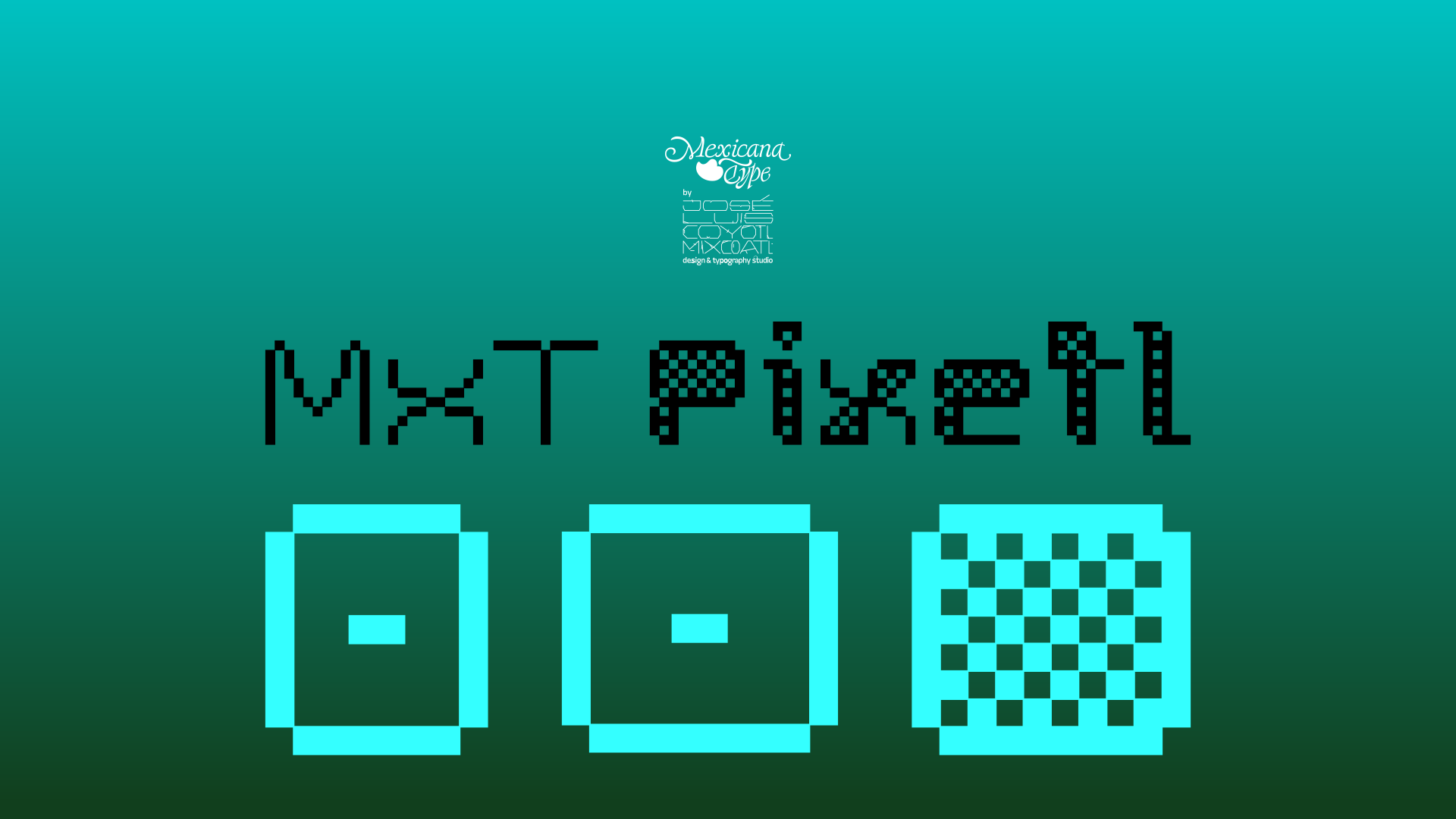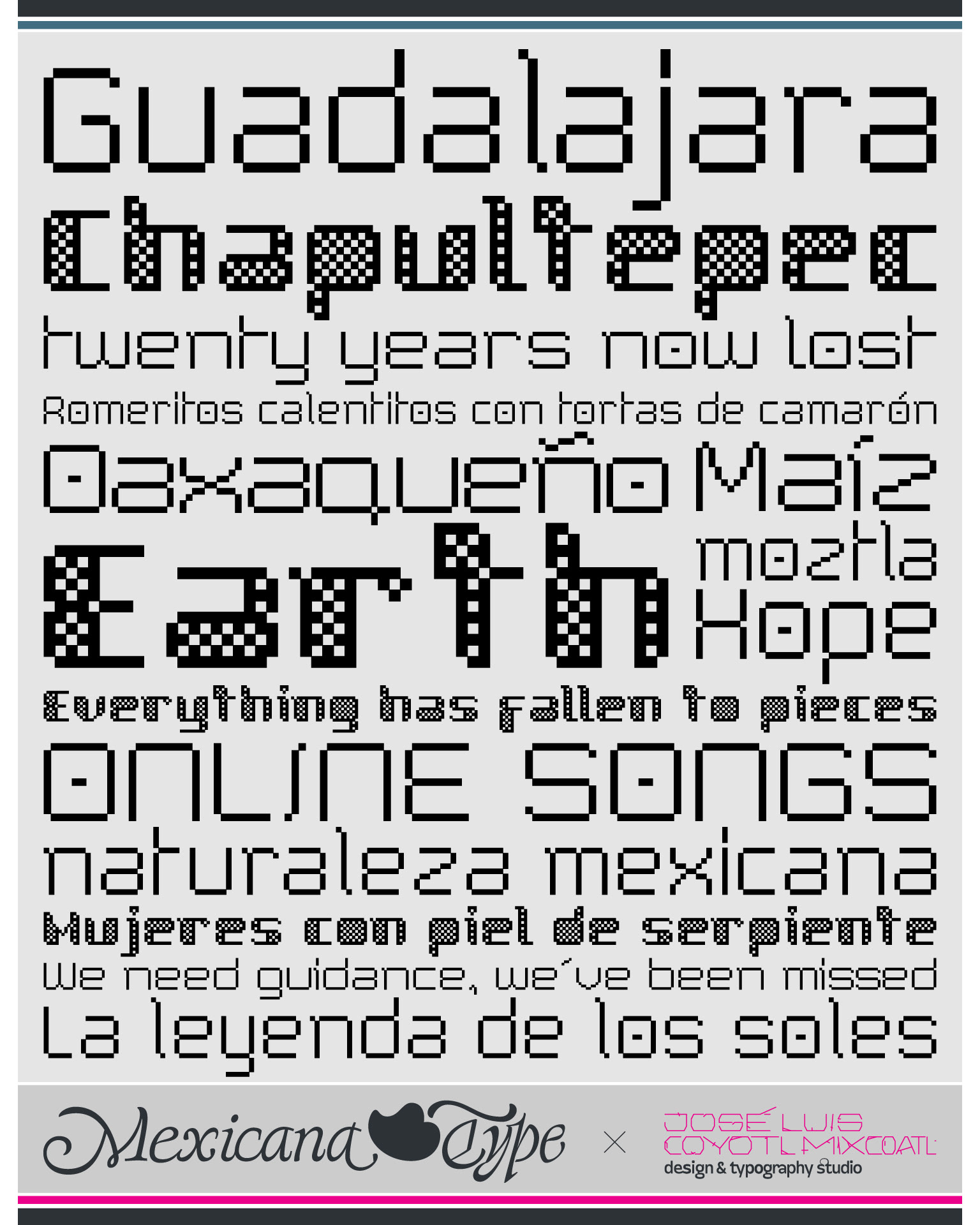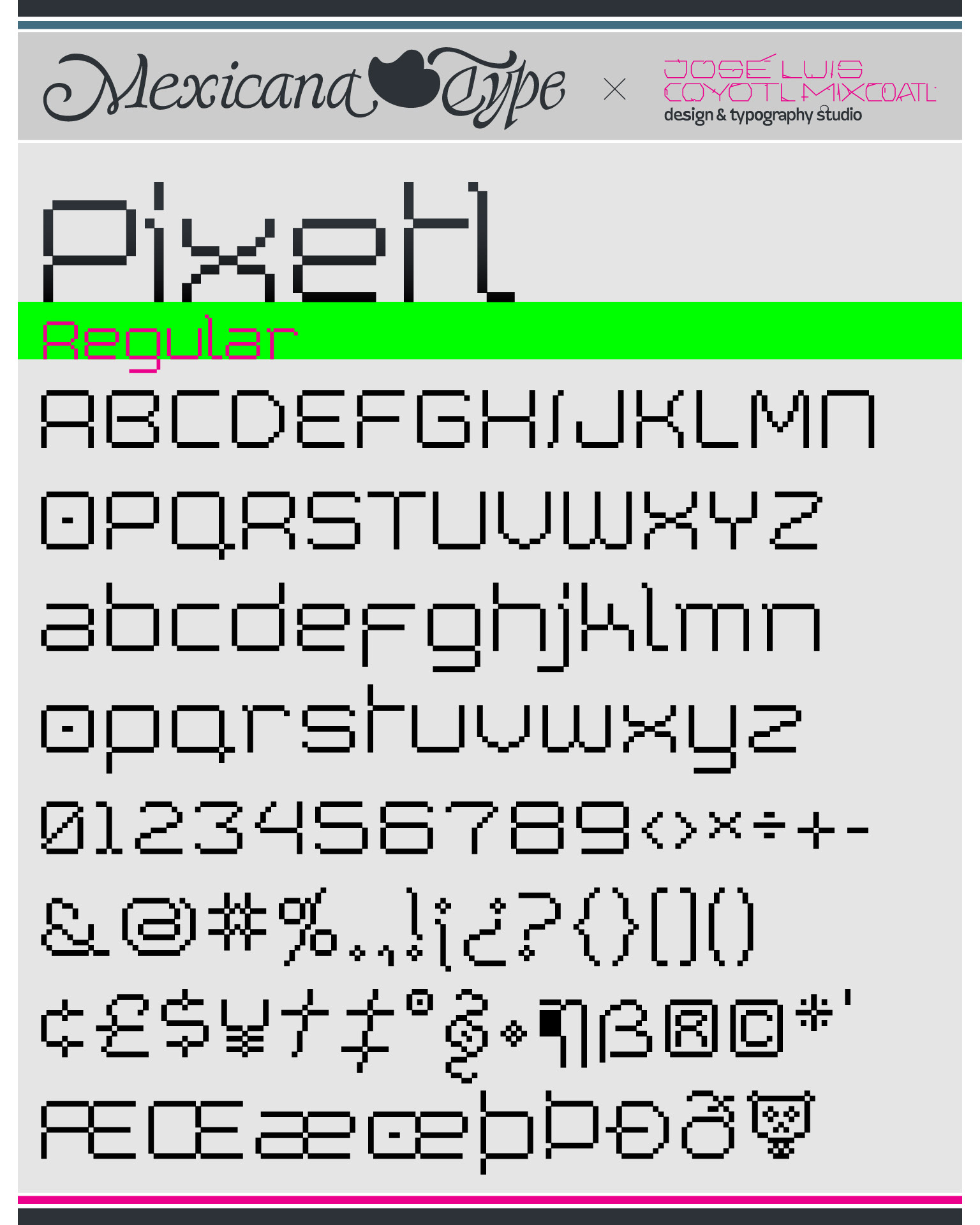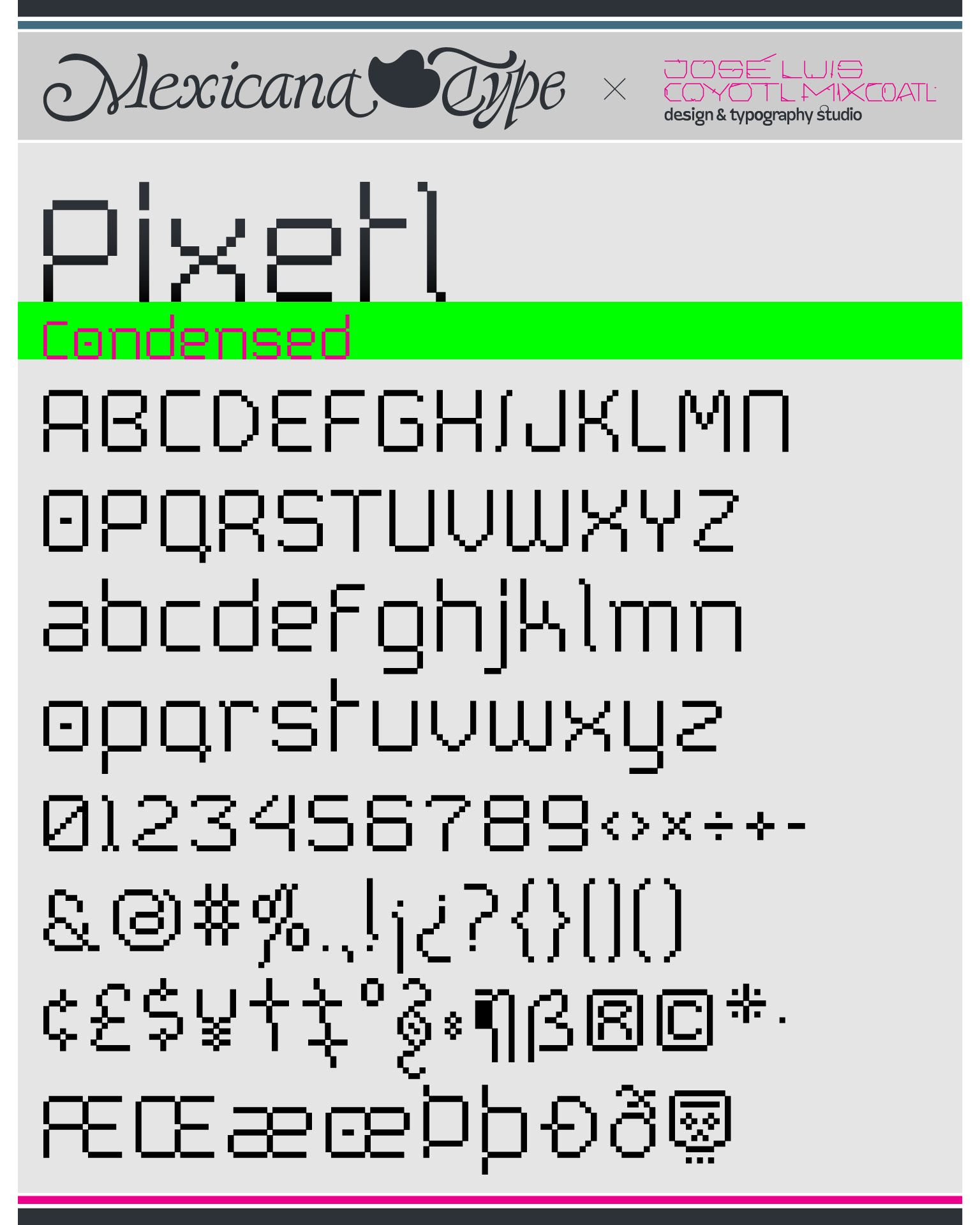
MxT Pixetl es una screen font modular, surge de una experimentación con pixeles y con una estructura de retícula y distribución de pequeños cuadrados y proporciones extendidas en sus caracteres, aunque tiene una variante condensada. MxT Pixetl consta de tres versiones: dos para cuerpo de texto para
pantalla, y otra más para títulos.